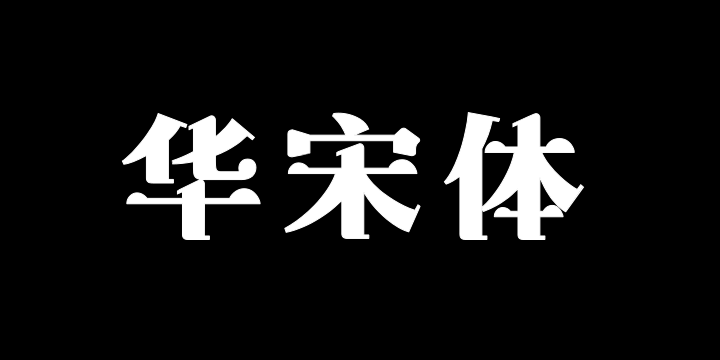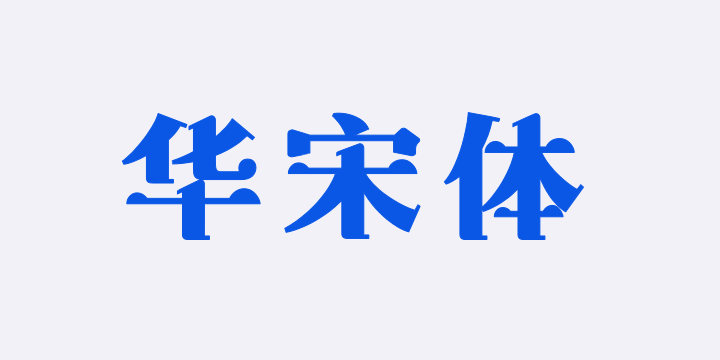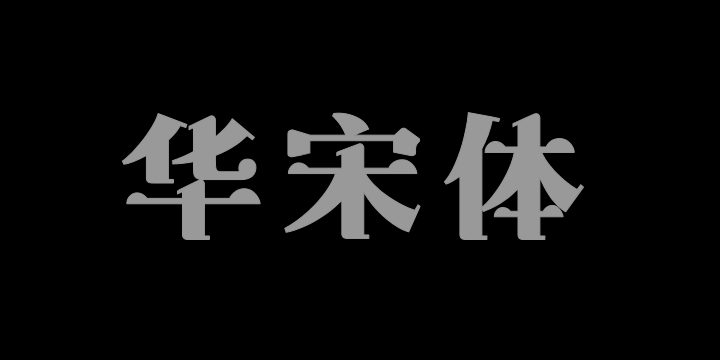
上首华宋体 By 上首造字 商用字体
字体全名: 上首华宋体
铸字厂: 上首造字
设计师: 胡博剑
字体简介: 上首华宋体,简体中文约6763字,在横画的始、末端添加了适度的装饰角,这些装饰角既不像传统宋体那样过于复杂和张扬,也不是完全简化掉,而是经过巧妙设计,大小和形状都较为适中,既为字体增添了一份传统的韵味,又不会显得过于繁琐,与现代审美相契合。整体字形呈现出方正的形态,给人以稳定、端庄的视觉感受,体现了宋体字的传统气质,适用于搭配标志、广告标语、商业广告等高端属性。